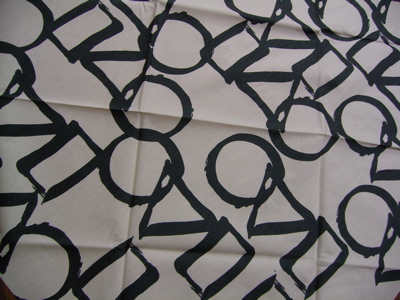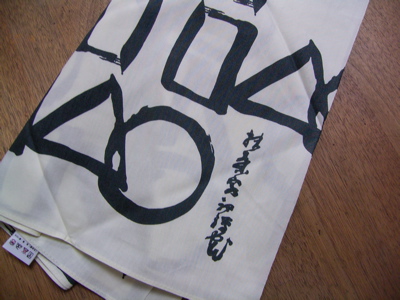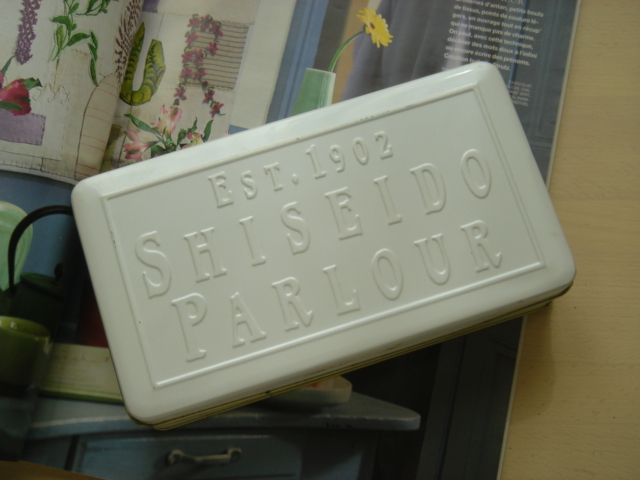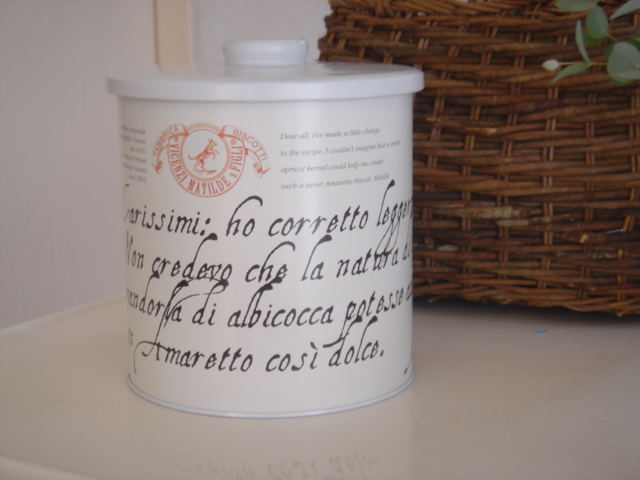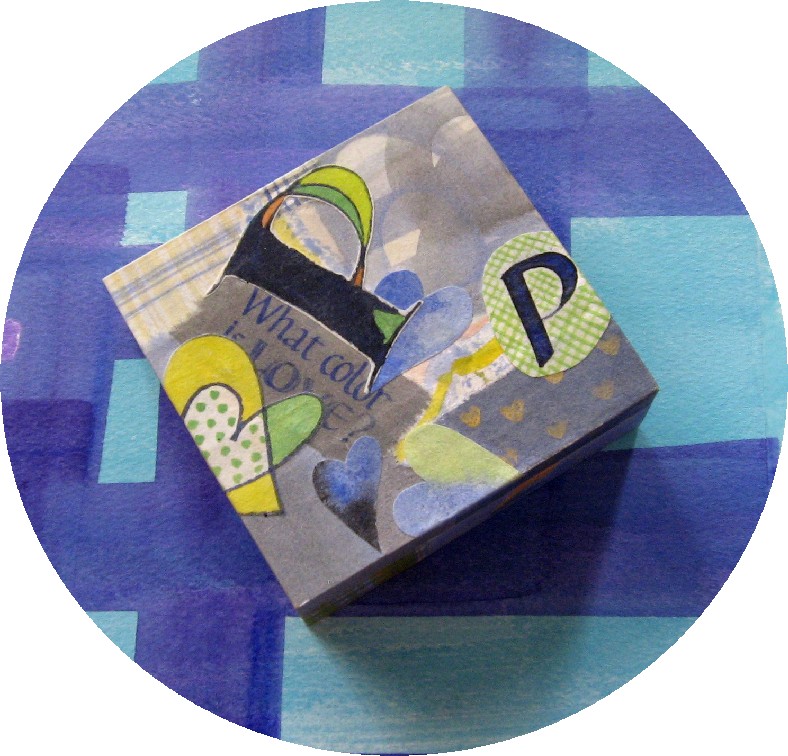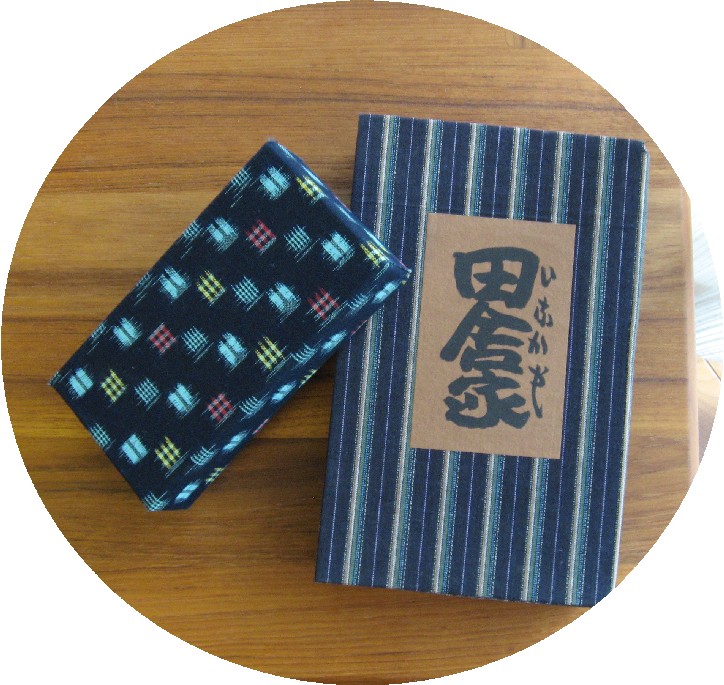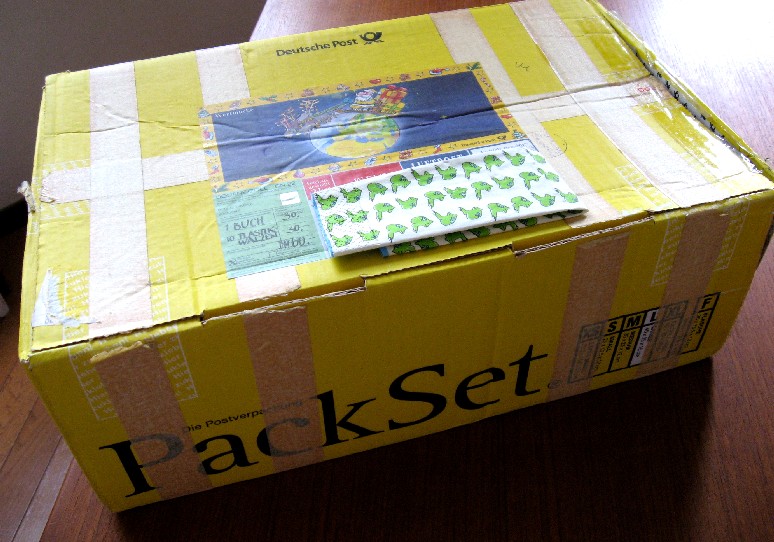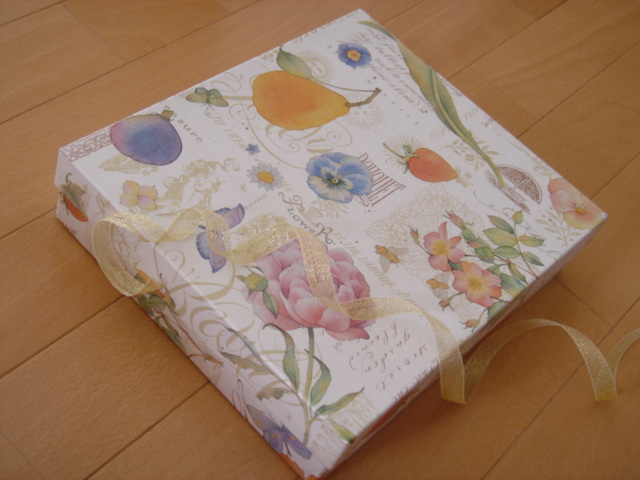
パッケージ
風呂敷活躍するの巻
先日hさんは○△□の飴をご紹介しましたが、私は風呂敷を買いました。
はい!この通り宇宙を表す○△□のオンパレードです。
このところ風呂敷はとても見直されていて、様々なデザインが出ていますが、センガイさんのこの風呂敷、白黒でかなりいいですよね!
今年の夏に海外旅行をしましたが、やはり日本人、トランクには荷物を風呂敷で包んで入れました。トランクの中でガサガサしないし、開けられても見苦しくないし、そのままクローゼットに入れられるし、あ〜ヤッパリ非常に便利。
これはイギリスで郵便局へ行くときの図。重たい荷物を運ぶ時も、風呂敷に包めばこんな風に二人で持てて便利です。助かるワ〜。
(おっと、ご覧下さい。この手前のお方は肩に荷物を担いでいらっしゃいますぞ!)
この風呂敷は、以前もご紹介したかもしれませんが、陶山由美さんデザインのDUAL
こんな包み方はちょっとお澄ましな感じで素敵。お風呂屋さんに行くというよりは、上等なお菓子か笹卷けぬき寿司(ささまきけぬきずし)が入ってる様なお姿です。
笹卷けぬき寿司は、元禄時代(赤穂浪士が討ち入りした年)に出来た古いふる〜〜いお寿司屋さんです。神田小川町にあります。
笹でまきまきしてあって、毛抜きで魚の骨を抜いたからたしかこんな名前だったような・・・?
ずっと、「ささまけ-ぬき寿司」と読んでいましたが、そうではなかった!
形はこんなんです。
ねっ!箱に入ったこんなお寿司、なんとなく由美さんの風呂敷が似合うでしょう〜? 笹巻けぬき寿司
現代のイギリスでも、江戸時代の神田でも風呂敷活躍するの卷でした〜!
続 お菓子の箱
さて、先週届いた宅急便。あら、お菓子?送り主はHさん。なぜに私に?
と包みをあけてみると、じゃ〜ん!これはこれは、「かまど」じゃないですか。
話題だった民芸調の包み紙です。興奮気味の私をもっと驚かせたのは同封のお手紙でした。
なんと送り主は、コメントでこのお菓子のパッケージのことを教えてくださった「しろさん」だったのです。
ただただ驚くばかりでした。
はい、これが、そのシンプルな黒い箱です。
確かに包み紙からは想像できないモダンな箱ですね。(包み紙はよく見るとかわいい模様が描かれています。昔から伝わるお菓子の型図だそうですよ)
箱の上にのせたのが中身のお菓子です。昔々の塩を作るときの「かまど」を模した形なのだそうです。お味も美味。ひよこに似ているけれど、皮がいい風味でとってもおいしいです。白餡もしっとり。
「名物 かまど」と
黒一色の上に赤が効いています。
ホント、素敵な箱です。
これも何かを入れる箱に…と、棚のコレクションに加えている
ラッピングペーパーとはんこ
きょうまで、鈴木泰子さんの個展が銀座伊東屋で開催されていますが、以前頂いたラピングペーパー(DMが包んでありました)、とても素敵で取っておいたのです。
おおきなサイズが印刷出来るプリンターを入手されてプリントしたものだそうです。うーん、そうか!ちょっと手間をかければこうして人を喜こばせる物が出来るのかもしれません。(でも、それにはもとのオリジナルのデザインが良くなくてはなりませぬ
)mojitor-hさんがとても得意のスキャン技とコピー技を使えば、予想以上に楽しいものが出来るかもしれません。
半紙に墨と筆でシンプルにThank youと繰り返し書いてあります。
中身がなくてこれだけ頂いても嬉しいかもー
これはイギリスのカリグラファー Mary Nobleさんから頂いた物です。嬉しいです!
封を開けようと裏を見てまたニンマリ。どなたかMary のために作って差し上げたのかしら?可愛い!可愛すぎる!このはんこ!
そう言えば昔カリグラファーのEwan Claytonに「遊庵」と書いたものを差し上げたことがありました。「ゆうあん」でも可愛いかったかもね。(でもちょっと、ゆうこりんみたいかも・・・?)
ひらがなのはんこは4文字だから形になるのかも。
日本人の女子の名前は3文字が多いからねぇ〜。いや、今時の名前は洗練されてるから、4文字も以外とあるのかもね〜。「さくらこ」とか、「かおるこ」とか?う〜ん、「こ」以外が付く4文字の名前ってないかしらん・・!?
まったくオーソドックスな3文字「子」付きの名前のmojitor-sでした。
箱のこと
先日、mojitor-fさんが「お菓子の箱」を紹介していました。
しろさんからのコメントで、高松の「かまど」の箱が話題に!
しろさん…私の両親は高松出身なのです…。
私が頂いたのはこの箱なんです。これにかまどのお菓子が入っていた記憶があるのですが…。ねぇ〜チョー民芸調でしょう?でも生地が渋くていい感じです!しろさんのは刻印のおしてあるシンプルなものなんですよねぇ?それも見てみたいわ!
ふと、見渡してみると私の周りにはmojtor-fさんのように可愛い箱がありません…。最近は靴の箱に何でも入れているからでしょうかぁ…。味気ない…。
でっかい箱ばかりの中で「ちょいカワ」なのが、これ!クリスマスシーズンにドイツから送られてきた箱です。ドイツポストの箱なので郵便局で買えるんですね…。サンタさんの絵がワクワク感を演出します。日本の郵政公社さんも、もう少しデザインを凝って頂ければ…と思う次第です。
この箱には、集めてしまったカードがゴチャ、ゴチャ入っています。
あまりに詰め込んだので最近は底が抜けそう…まずい!
さあ、さあ、何といってもチョーお気に入りは…、mojitor-fさんの手作りの箱!素敵ですよねぇ〜!彼女の繊細な色使いにはため息が出ます。箱に自作の文字やマークがコラージュしてあるんですねぇ〜。これにはアクセサリーを入れています。
いったいどんなところから発想するんでしょうか…。一度お話しをじっくり聞かせてねぇ…。
「いつの日にか…しろさんのかまどの箱を見てみたい…。」
mojitor-fさんとmojitr-hの二人言…でした。
お菓子の箱
涼しげゼリーをお土産にいただいたときの箱です。
あまりにきれいなので、箱好きの私はもちろん捨てられず、何か入れようかなあと考え中。
特にお店のロゴなどが入っていないので、一般的なギフト箱なのでしょうか。淡い色彩の中にいろいろな文字が入っていて、うふふと眺めてしまいます。よく見るとShakespeareとかBlakeのことば(詩)も書かれています。
お菓子のきれいな箱や缶には夢もいっぱいですね。
資生堂パーラーのクッキー缶は、ペンなど道具類が入っています。もうちょっと長さがあると、もっといろいろ入れられるのですけど、なんといっても文字が気に入っているので!
白色も大好きだし、ところどころ塗装がはげてますが、まだ捨てられません。よくワークショップにも連れて行きます。以前mojitor-sさんに紹介されていたアマレッティの円筒缶。これは、缶欲しさに自分で買いました。
ドッグフード1キロがぴったり入るのです。これなら部屋に出しておいてもOK、と思ったため・・・
え?中身のクッキーですか?はい、時間はかかりましたが、すべて食べました。
(と言ったらmojitor-tさんに呆れられてしまいましたー)